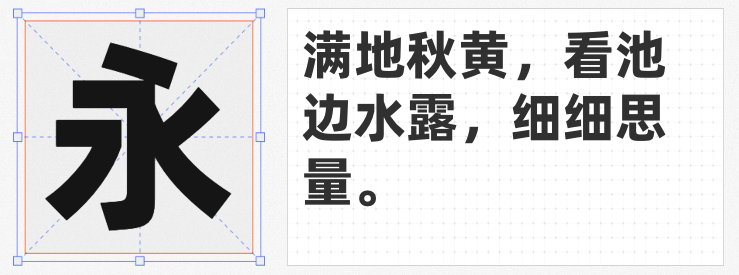
在电商直通车设计中,字体的选择至关重要,它不仅是信息传递的载体,更是塑造品牌形象、吸引用户注意力的关键元素。以下四款字体各具特色,能为电商直通车设计带来独特魅力。
1. 思源宋体 CN Bold
作为Adobe Type发布的最新泛CJK字体,它是思源黑体的宋体对应字体。这款字体线条粗壮有力,整体风格庄重典雅,又不失现代感。其丰富的字形设计,涵盖多种语言和字符,能满足电商直通车在不同地区、不同场景下的展示需求。在需要突出品牌文化底蕴或营造高端大气的氛围时,思源宋体 CN Bold是绝佳选择。
中文字体采用现代简洁的笔画,造型瘦长且重心较高,展现出20岁阿里巴巴少年的精气神。标题字省略出脚部分,更显简洁利落。这种设计风格符合当下年轻消费者的审美趋势,能够快速抓住他们的眼球。同时,其多字重的设计,可根据不同的设计需求灵活调整,无论是强调重点信息还是营造层次感,都能轻松胜任。
3. 文心喜乐体
这款字体具有极强的亲和力,随性而不拘谨。字形饱满,笔画错落有致,横竖粗细、比例结构对比明显,为字体增添了丰富的视觉变化。笔画中加入的高光纹理,增加了字体的肌理质感与趣味性,呈现出一种稚拙萌态。它既可用于标题,吸引用户注意力,也能作为正文,营造轻松愉快的阅读氛围,适用于多种电商直通车设计场景。
4. 小狼天穹
基于日本“解星计划”开发的“解星”字型衍生而来,以参照传承字形检校表修改的“宇文天穹”字体为基础,补制欠缺的繁简体字和注音符号。这款字体笔触适中,字形端正,具有很好的视觉感,适合应用于艺术设计、平面宣传设计等领域。在电商直通车设计中,它能展现出独特的艺术风格,为品牌增添一份独特的文化韵味。